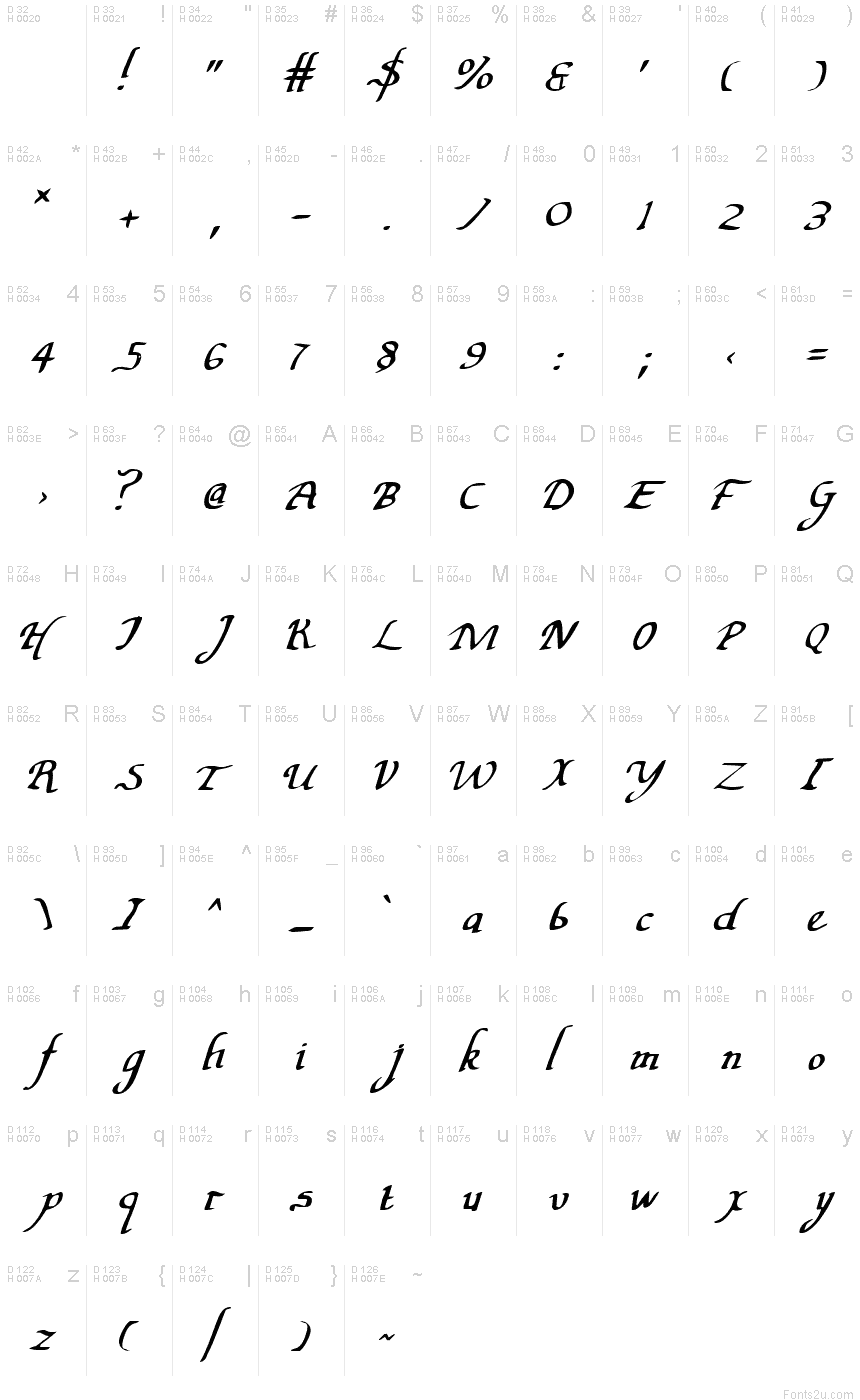
Valley Forge Italic od Iconian Fonts to darmowy, kaligraficzny krój pisma o szybkim, nostalgicznym charakterze. Litery są mocno pochylone i wyraźnie zwężają się ku końcom, łącząc szerokie pociągnięcia przypominające ruchy pędzla z ostrymi łączeniami. Nadaje to fontowi bardziej formalny, grawerowany klimat niż casualowe pismo.
Sprawdzi się w stylizowanym brandingu, na okładkach książek, plakatach, zaproszeniach i w menu restauracji, gdzie liczy się odrobina elegancji. Jako darmowy font, doskonale nadaje się też do krótkich nagłówków, inicjałów i szkiców logo, ponieważ długie, zdecydowane pociągnięcia dodają dynamiki i wyrazistości nawet krótkim słowom.